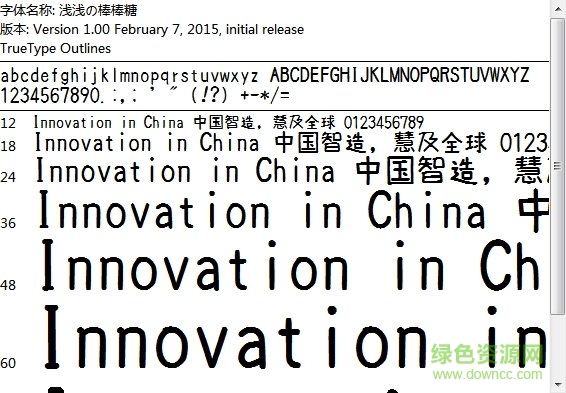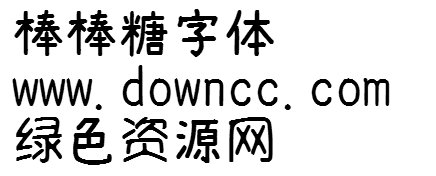
word棒棒糖字體
棒棒糖字體是一款有著卡通造型的藝術(shù)字體,在平面設(shè)計(jì)上較為廣泛,為大家?guī)?lái)優(yōu)秀的設(shè)計(jì)體驗(yàn),結(jié)構(gòu)和造型上都有著不錯(cuò)的視覺效果,快來(lái)綠色資源網(wǎng)試試吧!
word棒棒糖字體介紹
棒棒糖字體是淺淺制作的一款精品pop字體,兼具兒童字體和卡通字體的風(fēng)格,可以廣泛使用在各種兒童文字內(nèi)容的設(shè)計(jì)上,給用戶帶來(lái)更多的藝術(shù)體驗(yàn)。